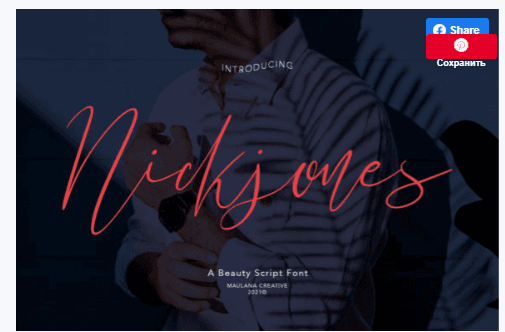
Nickjones Font
Nickjones - это восхитительный шрифт с танцующими и легкими персонажами. Он придаст изюминку любому дизайнерскому проекту, который вы желаете создать! Nickjones был специально создан для тех, кому нужен красивый и освежающий вид.